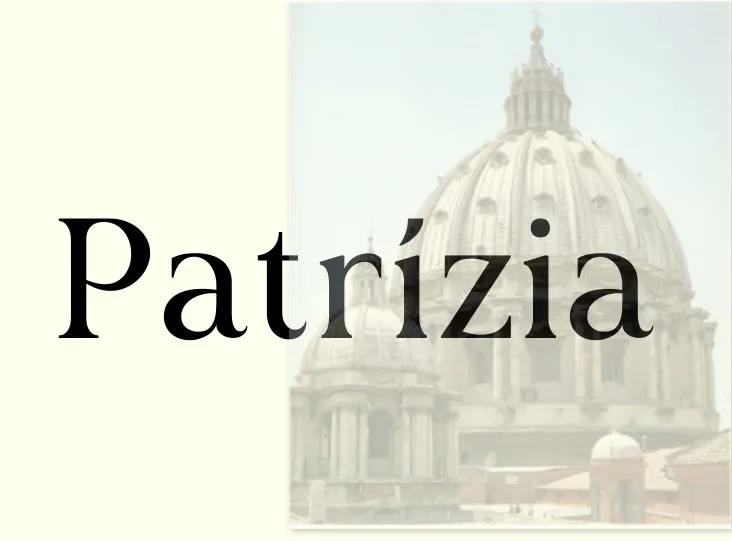
A fonte ‘Patrízia Font’ foi criada por Guilherme Bidarra e traz uma mistura sofisticada entre serif moderna inspirada no Renascimento italiano. Desenvolvida para atender tanto as estilizações modernas quanto às de olhar nostálgico, esta fonte se destaca pela sua elegância nos detalhes serifs e ligaturas que remetem à arquitetura italiana. Através do seu design refinado, a Patrízia Font oferece uma variedade extensa de caracteres incluindo diferentes alfabetos. Esta característica torna-a perfeita para designers que desejam estilizar textos tradicionais e modernos em um único layout, enquanto mantêm o tom sofisticado da fonte. Para quem gosta de transpor a elegância do Renascimento para aplicações digitais, Patrízia Font é uma escolha ótima. Seu design contemporâneo, que incorpora influências arquiteturais italianas na forma e no estilo dos serifs, oferece um equilíbrio entre antiguidade e modernidade. Adquirir a ‘Patrízia Font’ é adquirir não apenas uma ferramenta gráfica, mas também um elemento estético que pode dar vida às suas ideias em diversos formatos de mídia digital. Sua versão moderna e sofisticada traz um toque inigualável ao seu trabalho, tornando-a ideal para criações que precisam de um toque de elegância clássica.